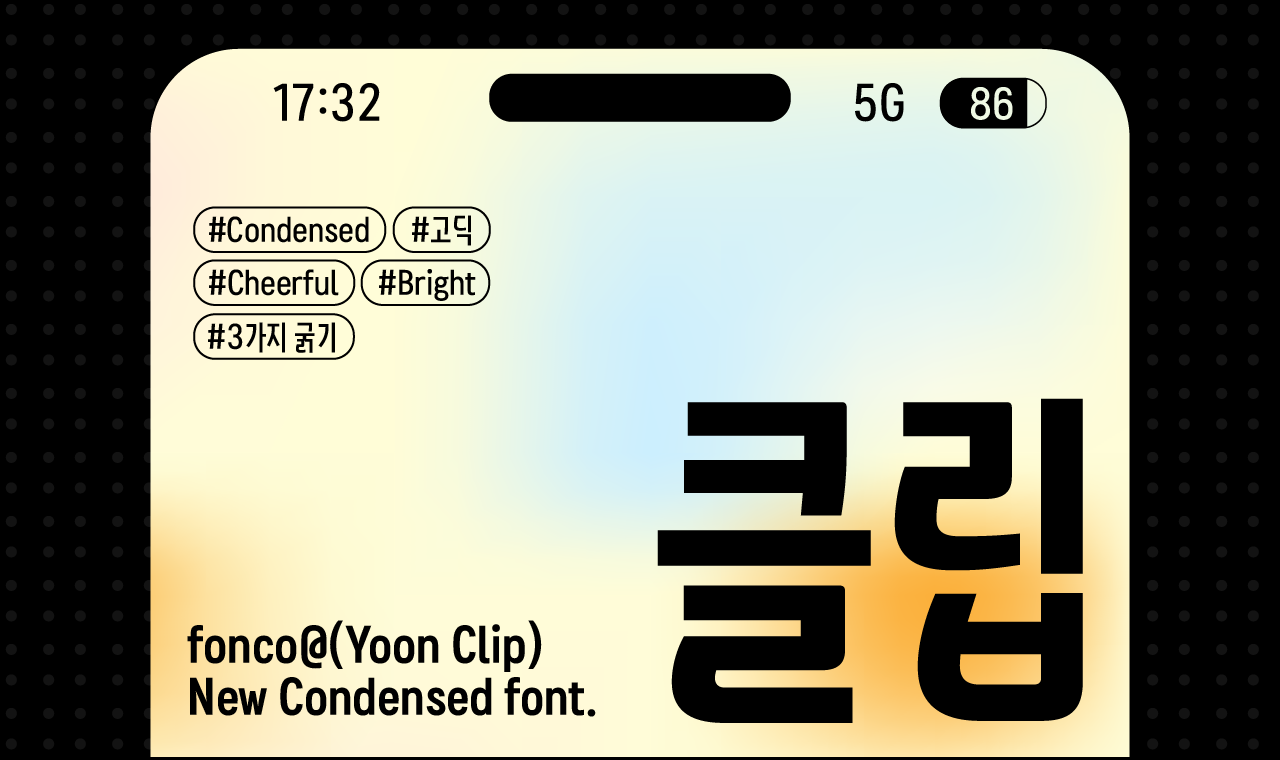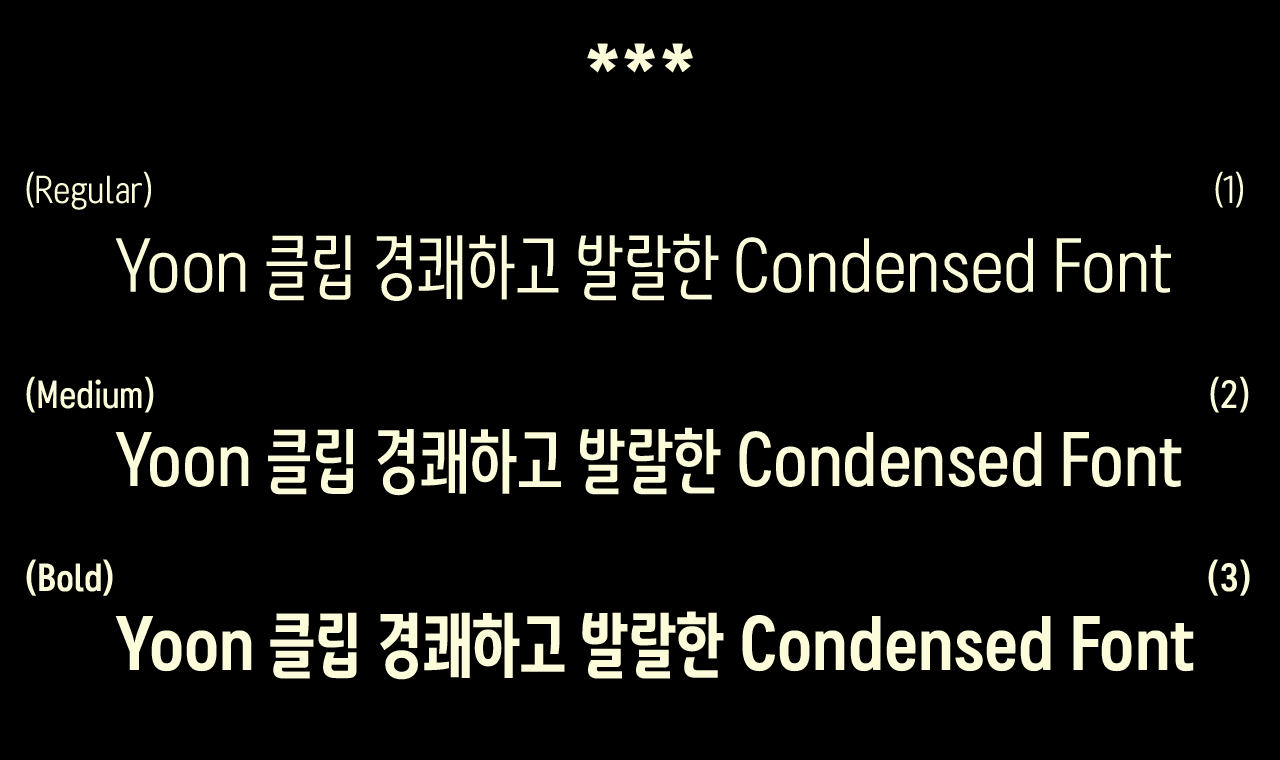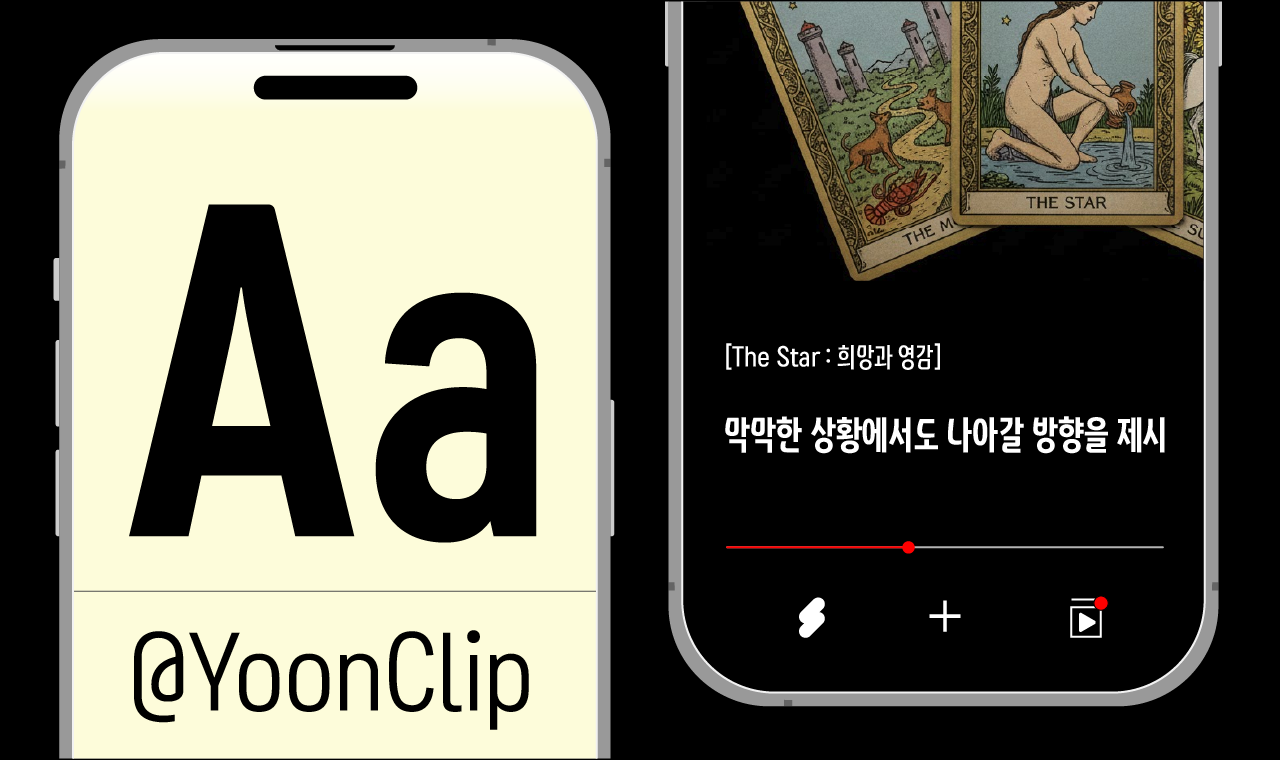
클립
Yoon 클립
Yoon 클립은 장체 스타일의 캐주얼한 고딕 서체입니다. 글자 폭을 효율적으로 설계하여 좁은 모바일 화면에서도 많은 정보를 깔끔하게 전달합니다. 영상의 핵심을 담아낸 클립처럼, 당신의 소중한 하이라이트를 Yoon 클립으로 더 선명하게 기록해 보세요.